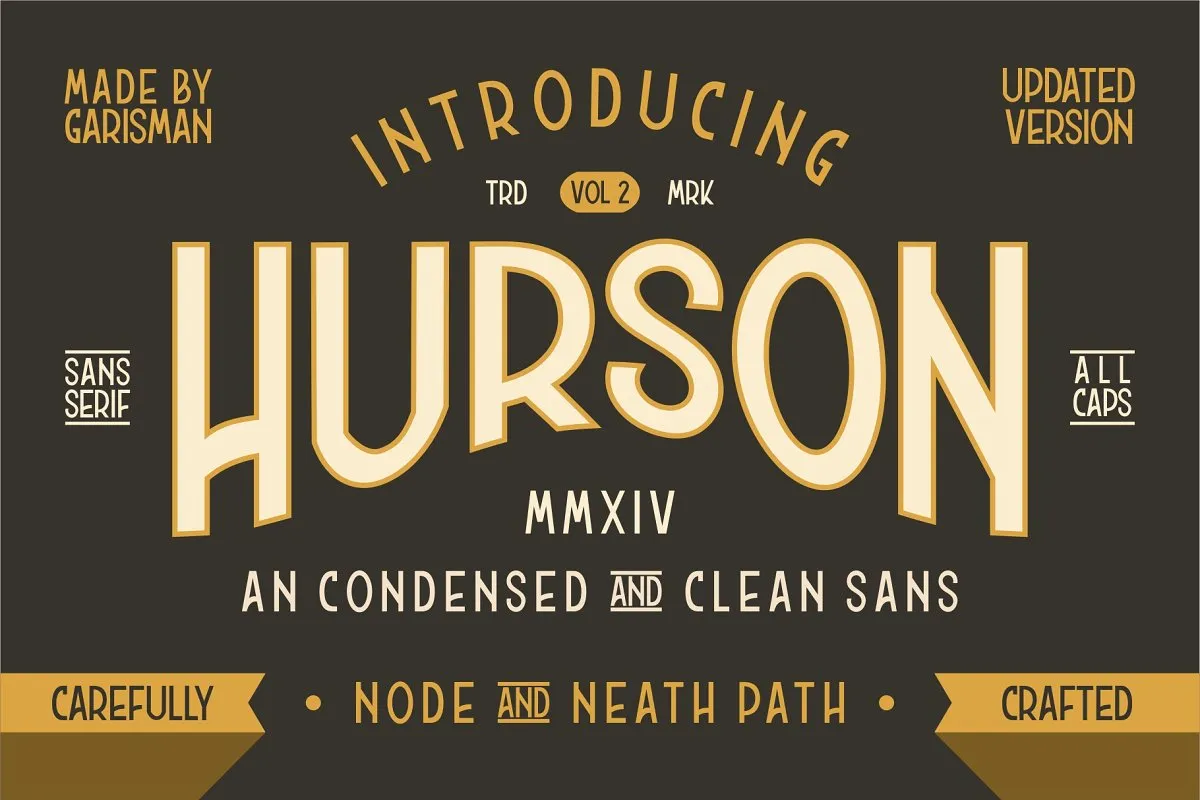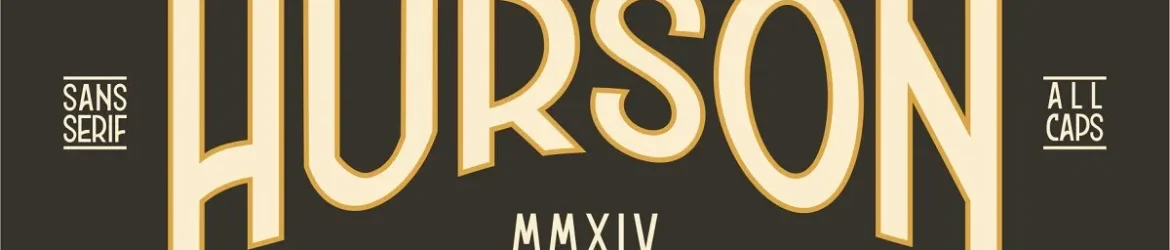
A fonte ‘Hurson Clean Typeface’ é uma tipografia sem serif altamente condensada e limpa, perfeita para criar um estilo moderno que se adapta a diversas necessidades de design gráfico. M.0Type concebeu esta fonte com uma mistura sofisticada de elementos antigos e contemporâneos, proporcionando um ar vintage sem parecer antiquado. O designer Garisman Std criou o Hurson Clean, um dos dois estilos desta fonte que inclui também o mais recente Hurson Rough. A ‘Hurson Clean Typeface’ transmite uma sensação de elegância clássica e arte manual com a mesma facilidade. Ideal para aplicativos variados como materiais de marca, camisas personalizadas, impressão em série, cartões de visita, logotipos, outdoors, t-shirts, fotografia e citações. Esta fonte já foi pré-encodada para PUA, tornando-a uma escolha perfeita para quem busca um design vintage ou uma aparência aquarela. É adaptável a quase qualquer tipo de projeto gráfico que deseje dar vida à sua ideia única.